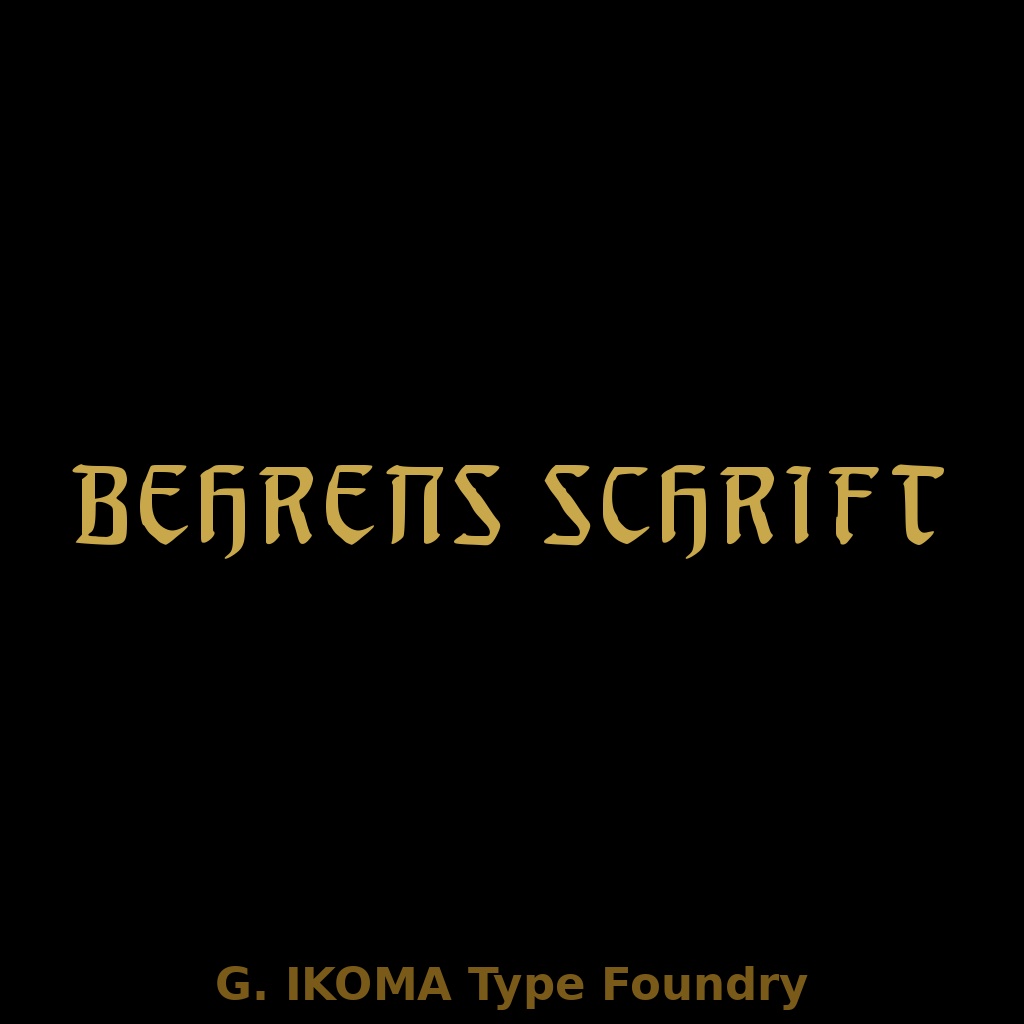
BEHRENS SCHRIFT — 19世紀欧州印刷資料復元フォント / Historical Revival Typeface [Jugendstil]
━━━━━━━━━━━━━━━━━━━━━━━━━ 【フォントについて】 ━━━━━━━━━━━━━━━━━━━━━━━━━ **BEHRENS SCHRIFT** は、19世紀末〜20世紀初頭の欧州印刷資料を原典に、手作業でトレース・デジタル化した復元フォントです。 本作は、建築家・デザイナー **Peter Behrens** が設計し、**Rudhardsche Giesserei, Offenbach a.M.** により製造された Jugendstil 書体をもとに再構成したものです。原典資料には **「ORIGINALERZEUGNIS DER RUDHARDSCHEN GIESSEREI」** と記されています。 幾何学性と装飾性をあわせ持つ字形が特徴で、ユーゲントシュティールから近代デザインへの移行期を感じさせる書体です。 **原典**:Ludwig Petzendorfer, *Schriften-Atlas* または *Schriften-Atlas: Neue Folge* Julius Hoffmann, Stuttgart(パブリックドメイン) **様式**:Jugendstil **収録文字**:大文字 A–Z、小文字 a–z、数字 0–9、記号類 **欠落文字**:なし **制作**:株式会社生駒時計店 / G. IKOMA, LTD.(1870年創業) ━━━━━━━━━━━━━━━━━━━━━━━━━ 【ご購入前にご確認ください】 ━━━━━━━━━━━━━━━━━━━━━━━━━ 本フォントは、装飾性と独特の造形を特徴とする **ディスプレイ向け書体** です。 ロゴ、見出し、ポスター、装丁、パッケージなどには適していますが、本文組版や小サイズでの長文用途には向きません。 また、原典由来の字形をもとに再構成しているため、現代的な本文用書体のような汎用性を前提とした設計ではありません。 ━━━━━━━━━━━━━━━━━━━━━━━━━ 【収録内容】 ━━━━━━━━━━━━━━━━━━━━━━━━━ ・BEHRENS_SCHRIFT.ttf ・LICENSE.txt ━━━━━━━━━━━━━━━━━━━━━━━━━ 【推奨用途】 ━━━━━━━━━━━━━━━━━━━━━━━━━ ・ロゴ ・見出し ・ポスター ・パッケージデザイン ・書籍タイトル ・装丁 ・ラベル ・バナー画像 ・サムネイル画像 **装飾性を活かすディスプレイ用途** に適しています。 本文組版や小サイズでの常用には向きません。 ━━━━━━━━━━━━━━━━━━━━━━━━━ 【ライセンス】 ━━━━━━━━━━━━━━━━━━━━━━━━━ 本フォントは、**個人利用・商用利用を問わず**、印刷物、画像、ロゴ、バナー、動画サムネイル等の制作に使用できます。 また、**WebサイトやSNSで画像化された状態で使用することは可能**です。 ただし、以下の行為は禁止します。 ・フォントファイルそのものの再配布、再販売、譲渡、共有 ・改変したフォントファイルの配布 ・本フォントを素材集、テンプレート、デジタル商品等に収録して再販売する行為 ・**本フォントファイルをWebフォントとしてサーバーに設置・配信して利用する行為** ・アプリケーション、ゲーム、ソフトウェア、電子機器等への埋め込み利用 ・AI学習、機械学習、生成モデル訓練等への利用 ・本フォント自体または収録字形そのものについて独占的権利を主張する行為 詳細は同梱の **LICENSE.txt** をご確認ください。 ━━━━━━━━━━━━━━━━━━━━━━━━━ 【原典資料について】 ━━━━━━━━━━━━━━━━━━━━━━━━━ 本フォントは、G. IKOMA, LTD. 所蔵の実物資料をもとに制作しています。 原典資料そのものは本商品に含まれていません。 資料アーカイブについては、下記サイトをご参照ください。 G. IKOMA Archive [https://g-ikoma-archive.netlify.app/](https://g-ikoma-archive.netlify.app/)